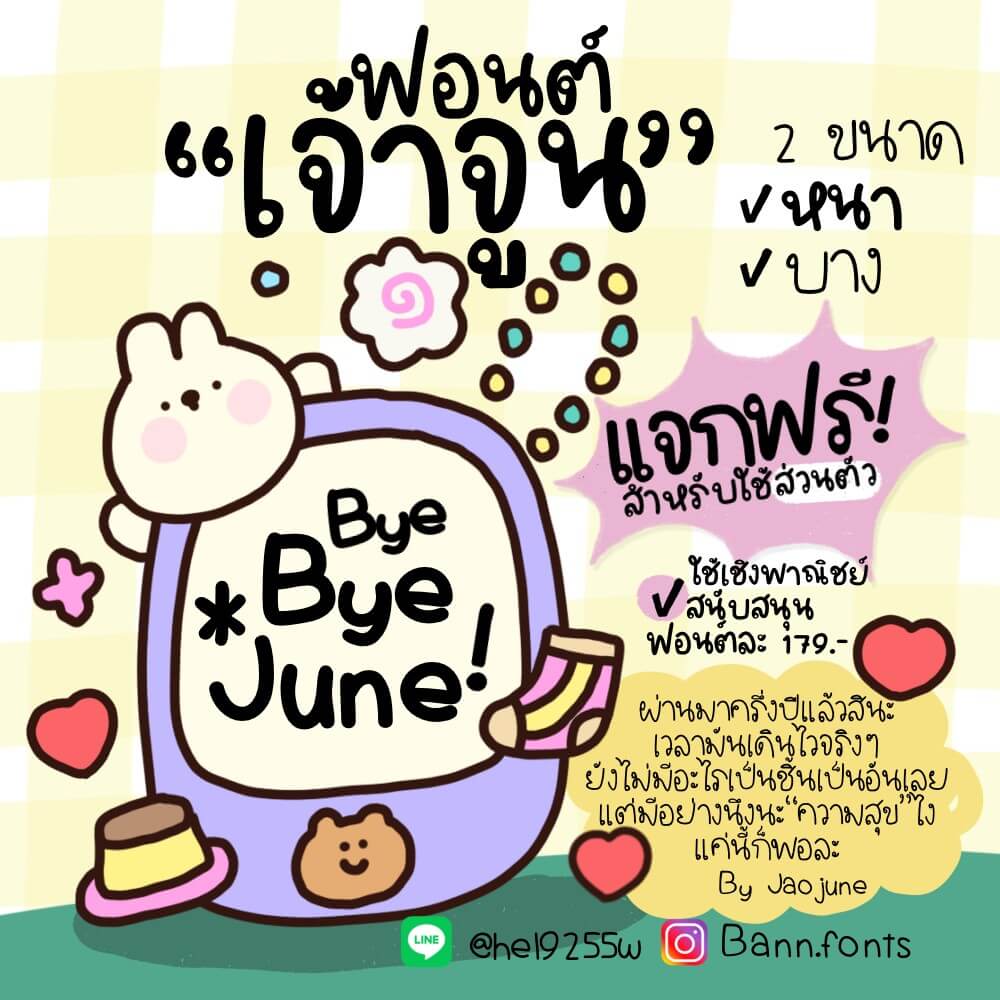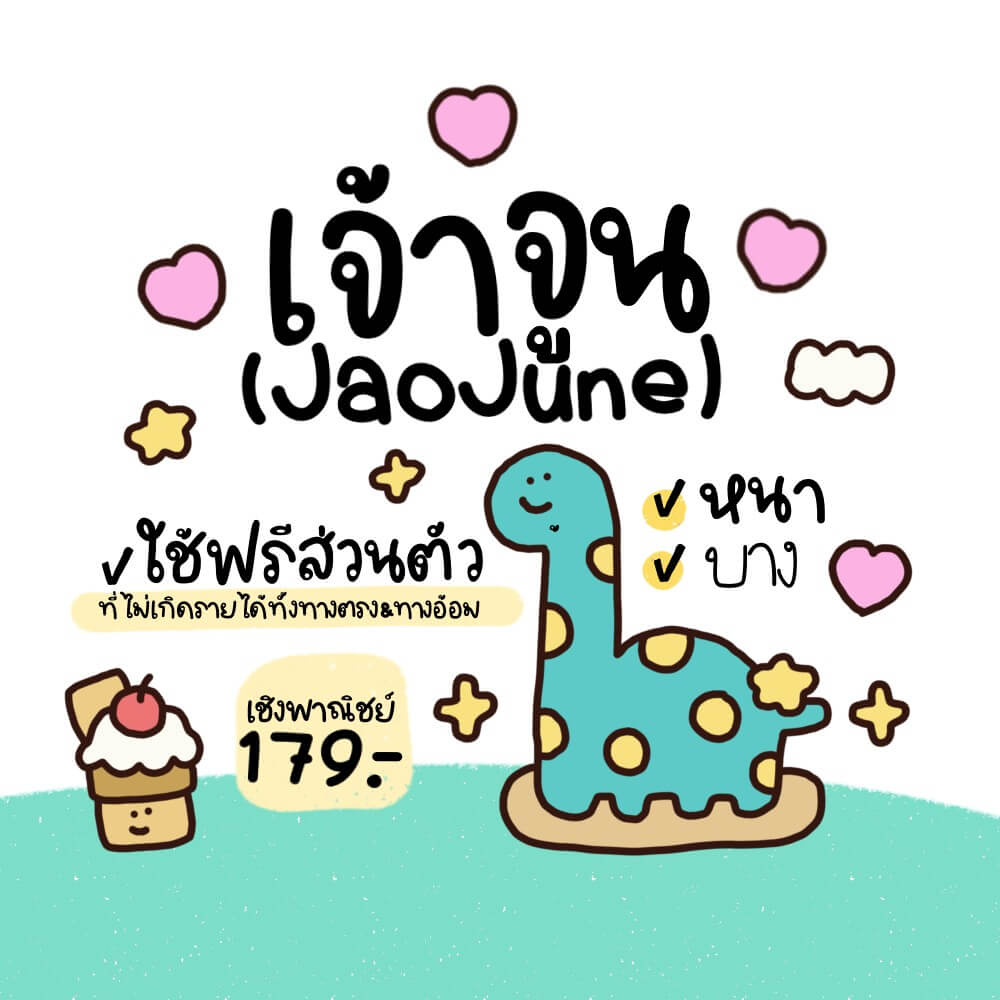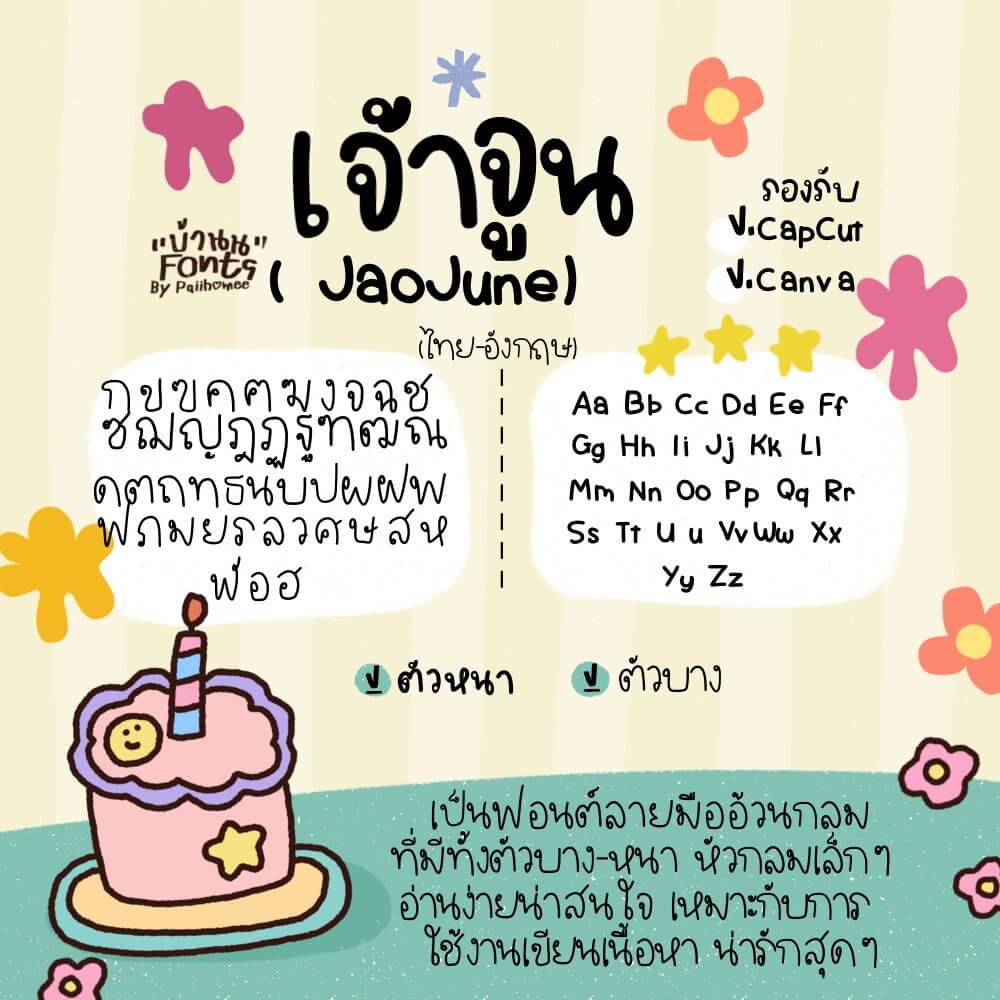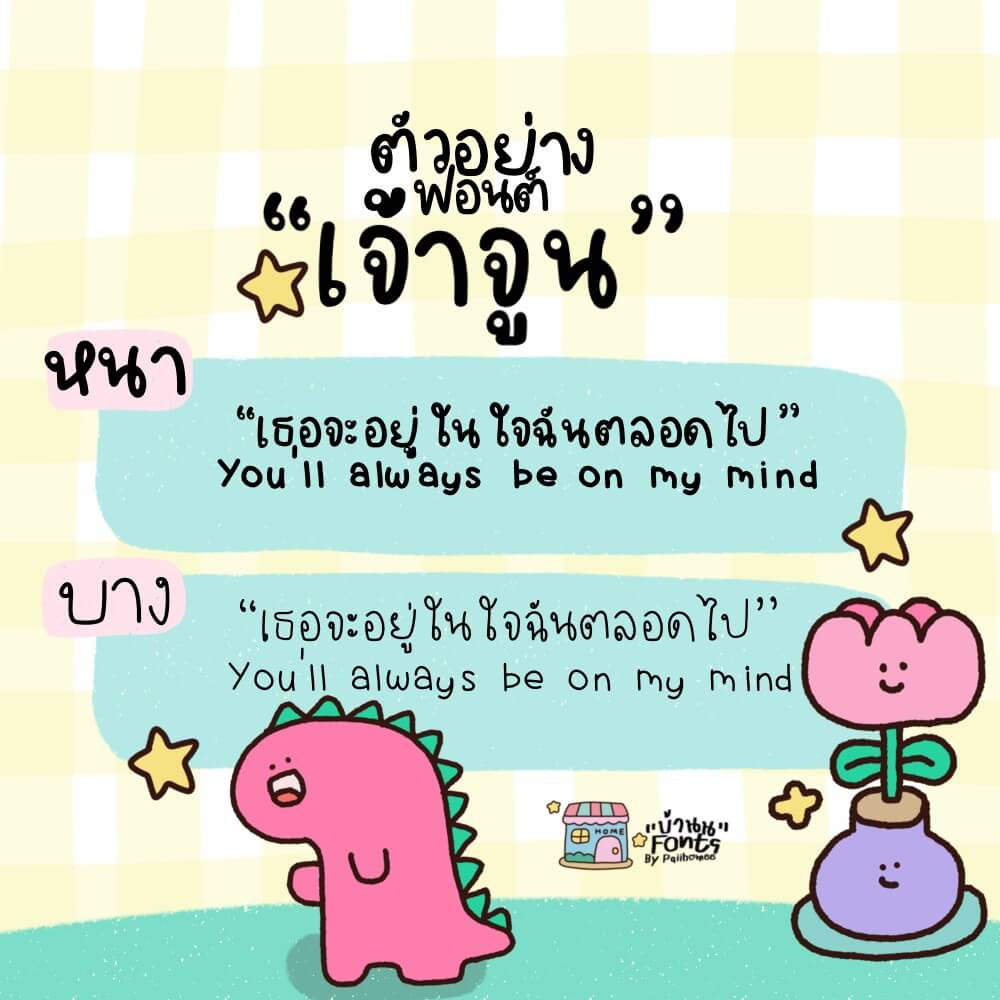
ฟอนต์ เจ้าจูน แจกฟรี! ✔️ใช้งานส่วนตัว เป็นฟอนต์ตัวอ้วนกลม อ่านง่าย น่ารักโดดเด่นเป็นเอกลักษณ์ มี 2 น้ำหนักเส้น เส้นหนาและ เส้นบาง
ไม่มีเลขไทย (๐๑๒๓๔๕๖๗๘๙)